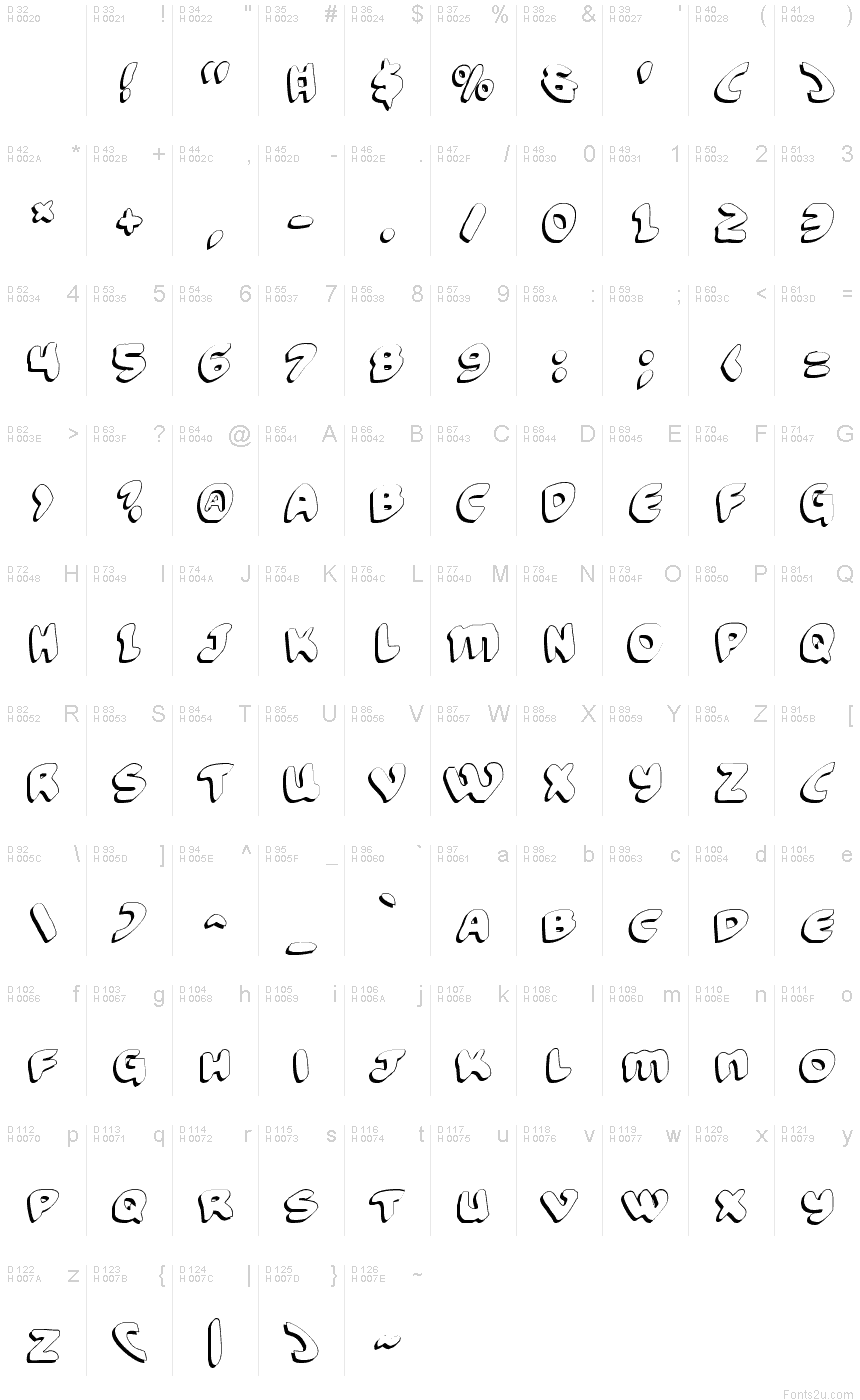
Funny Pages Shadow od Iconian Fonts to darmowy komiksowy krój displayowy z dużymi, napompowanymi literami, które wyglądają jak wyjęte prosto z niedzielnego paska komiksowego. Każdy znak jest miękki i przyjemny, podkreślony wyraźnym czarnym cieniem, dzięki któremu tekst wygląda na stronie jak naklejka. Rytm pisma jest luźny i skoczny, nadając nagłówkom zabawną, przystępną energię, która pozostaje czytelna nawet w dużym rozmiarze.
Ten darmowy font świetnie sprawdzi się na okładkach książek dla dzieci, ulotkach szkolnych, zaproszeniach na urodziny, w komiksach, na opakowaniach zabawek czy w kreatywnych logotypach, gdzie liczy się śmiały i przyjazny przekaz. Użyj Funny Pages Shadow w dużej skali, aby masywne kształty i wyrazisty cień mogły w pełni wybrzmieć; zestaw go z czystym krojem bezszeryfowym w tekście głównym, aby zachować czytelność, podczas gdy tytuł zajmie się całą zabawą.
Funny Pages Shadow
Dan Zadorozny